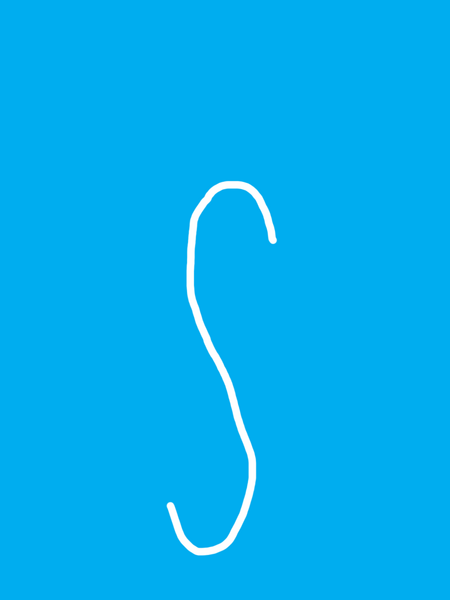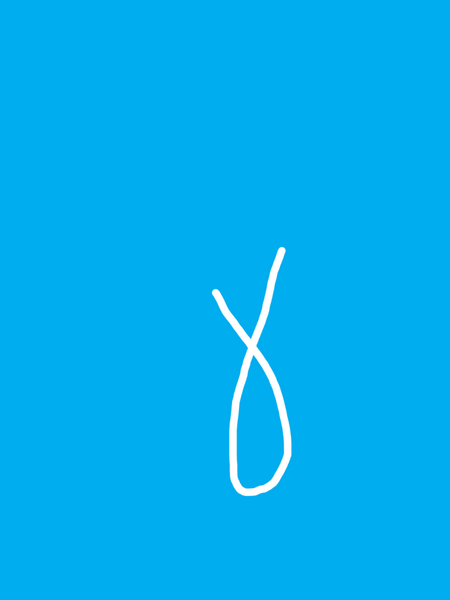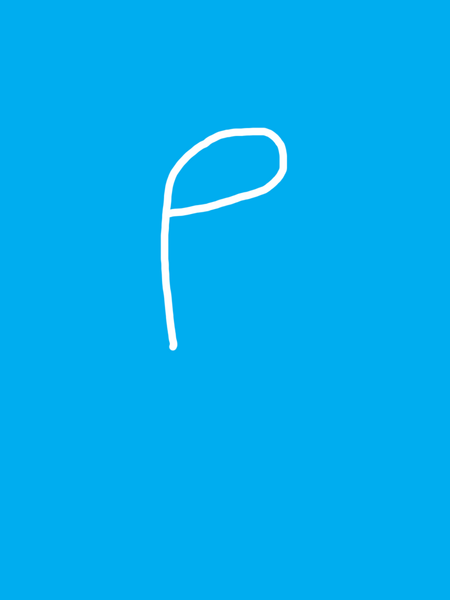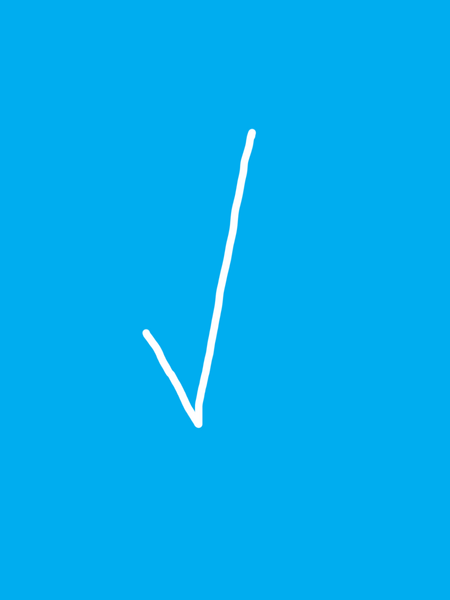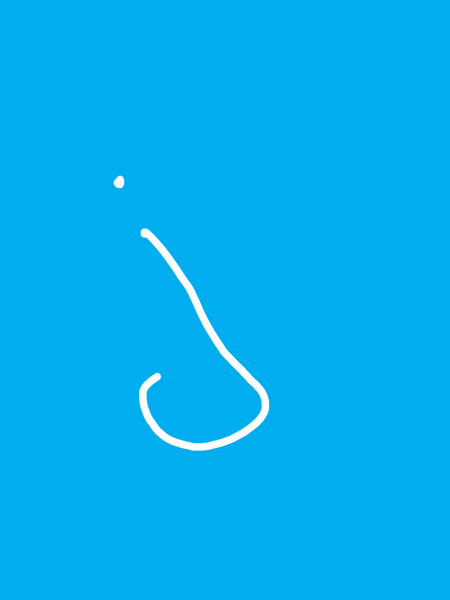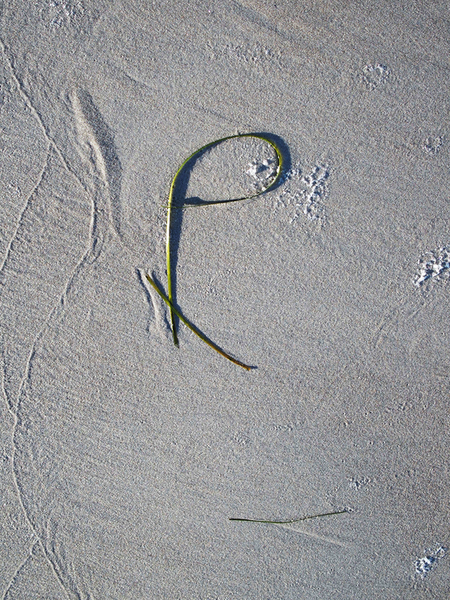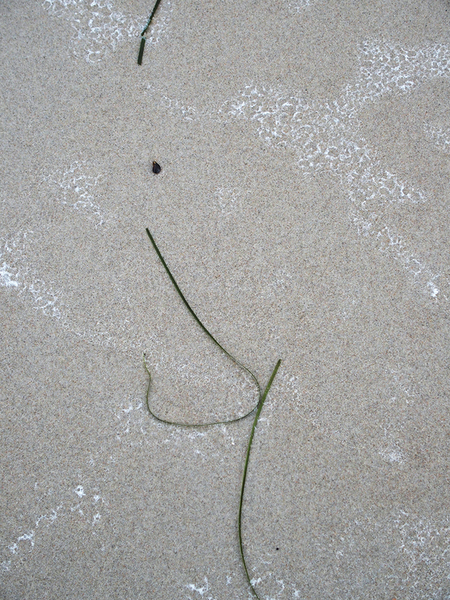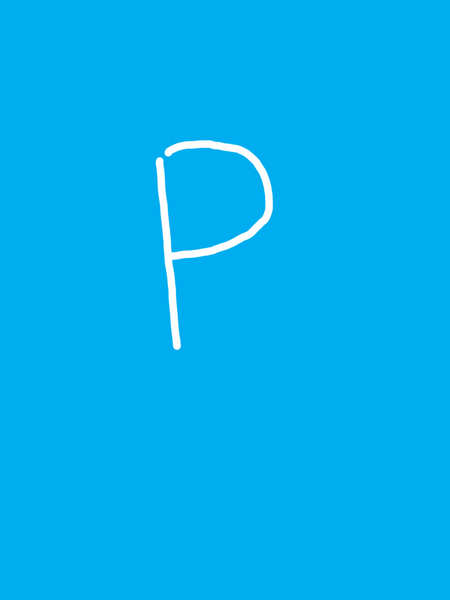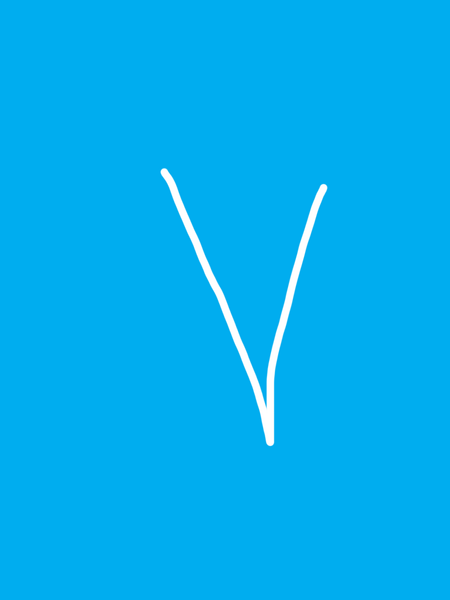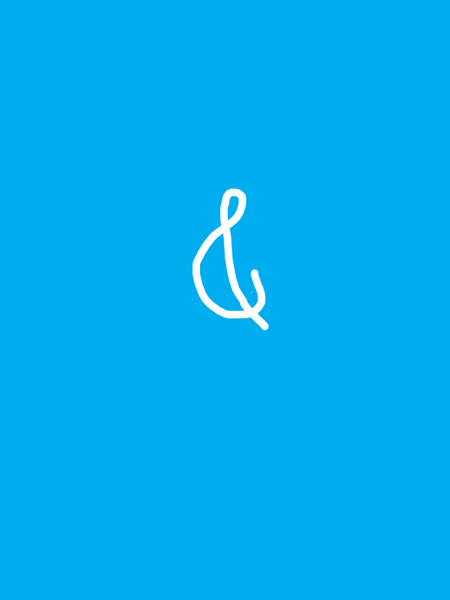
Ostseetypografie Teil 1 - Seegras-Typografie
Das Meer (in dem Falle die Ostsee am Strand der Insel Rügen) formt mit Wellen und Wind per Zufall aus Seegras kalligrafische Buchstabenformen. Dies fiel mir bei zahlreichen Herbstspaziergängen am Strand von Thiessow (Mönchsgut/Rügen) auf. Diese Beobachtung galt es genauer zu untersuchen und zu beobachten.
Dabei fiel auf, dass bestimmte Buchstabenformen besonders häufig zu finden waren. Dies betraf das griechische Alpha oder Gamma und das ganz „normale“ U. Oft waren die Buchstaben nur für wenige Sekunden sichtbar, bis die nächste Welle die Form schon wieder veränderte oder ganz zerstörte.
So hatte ich ein schön geschwungenes großes „V“ entdeckt. Schon die nächste Welle magerte es ab zu einem relativ schmalen „V“. Die zweite Welle ließ es dann ganz verschwinden. Philosophisch gesagt lagen also das „Entstehen“ und „Vergehen“ der aus dem Meer geborenen Zeichen ganz dicht beieinander.
Eine Bemerkung sei noch erlaubt. Keine (und ich schwöre wirklich keine) der Buchstaben- oder Zeichenformen, die ich beobachtet und fotografiert oder gefilmt habe, wurde mit der Hand gelegt oder irgendwie nachträglich manipuliert.
Alles war das Produkt von Meer und Wind und einfach nur schön.